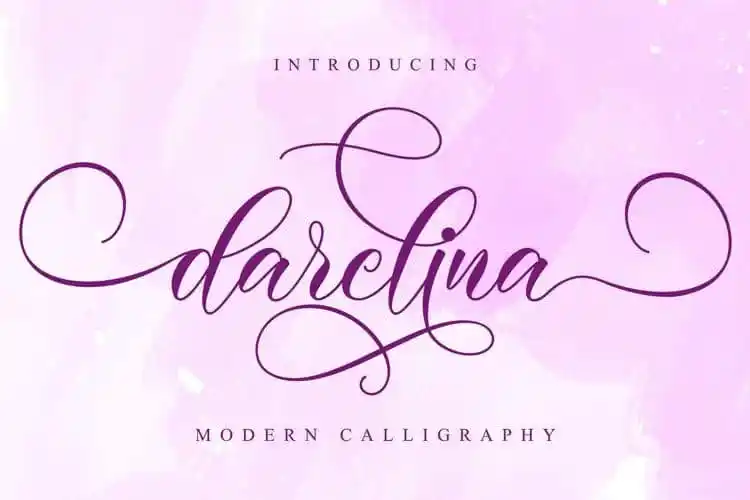
Darelina Calligraphy Font – Download Grátis
Darelina Calligraphy Font é uma fonte elegante e formal com raízes clássicas e toques românticos perfeitos para projetos que buscam um ar sofisticado. Especialmente adequada para criações como cartas de agradecimento, anúncios e até mesmo headlines, essa fonte atingiu uma nova dimensão com sua versatilidade. Desenvolvida pelo Nissa Studio em 99designs, Darelina oferece um toque moderno e perfeito para aqueles que buscam uma combinação harmoniosa entre a simplicidade clássica e o refinamento contemporâneo. Sua elegância se manifesta de maneira surpreendente nas mais diversas aplicações gráficas, garantindo um toque romântico em qualquer projeto que escolha para si.